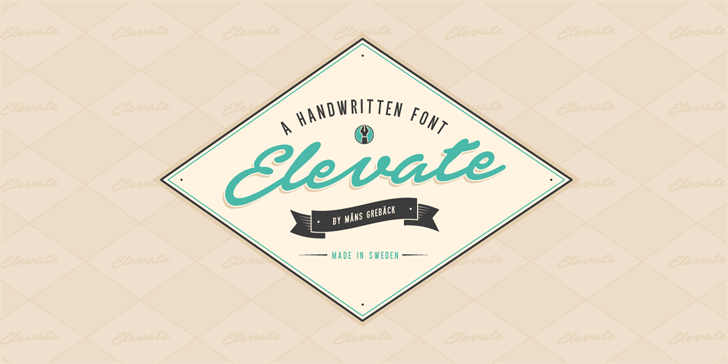
A elevada font ‘Elevate’, criada pelo designer Måns Grebäck em 2016, é uma opção perfeita para quem busca uma fonte com estilo erudito e elegante. Este tipo de letra tem uma aparência clássica que se adapta bem a diversas aplicações, desde design gráfico até criação de produtos pessoais. Se você está procurando por um recurso gráfico elegante sem grandes investimentos financeiros, ‘Elevate’ é um excelente escolha. Para uso personalizado apenas, esta fonte oferece uma variedade de linhas e opções estilísticas que podem ser usadas para aumentar a visibilidade de seu trabalho ou produto, sempre mantendo um tom distinto e sofisticado. O designer Hamilton agora apresenta esta fonte aos usuários brasileiros, expandindo ainda mais o alcance da elevada funcionalidade deste tipo de letra única.